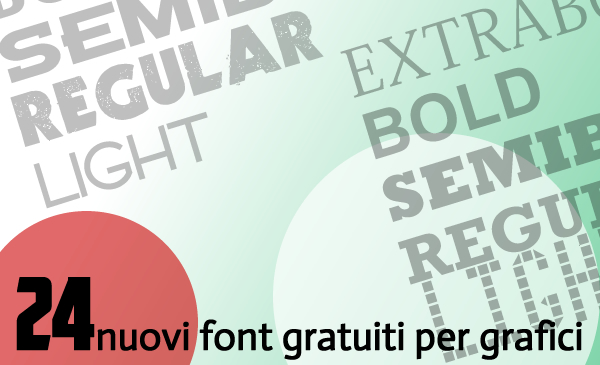
Sul sito Graphic Design Junction, vi segnalo una bella raccolta di 24 font gratuiti utili per i grafici.
Tutti i font sono di alta qualità , perfetti per logotipi, marchi e qualsiasi tipo di grafica tipografica.
In questa raccolta troverete sicuramente i font più adatti per rendere il vostro design più professionale.
24 nuovi font gratuiti per grafici